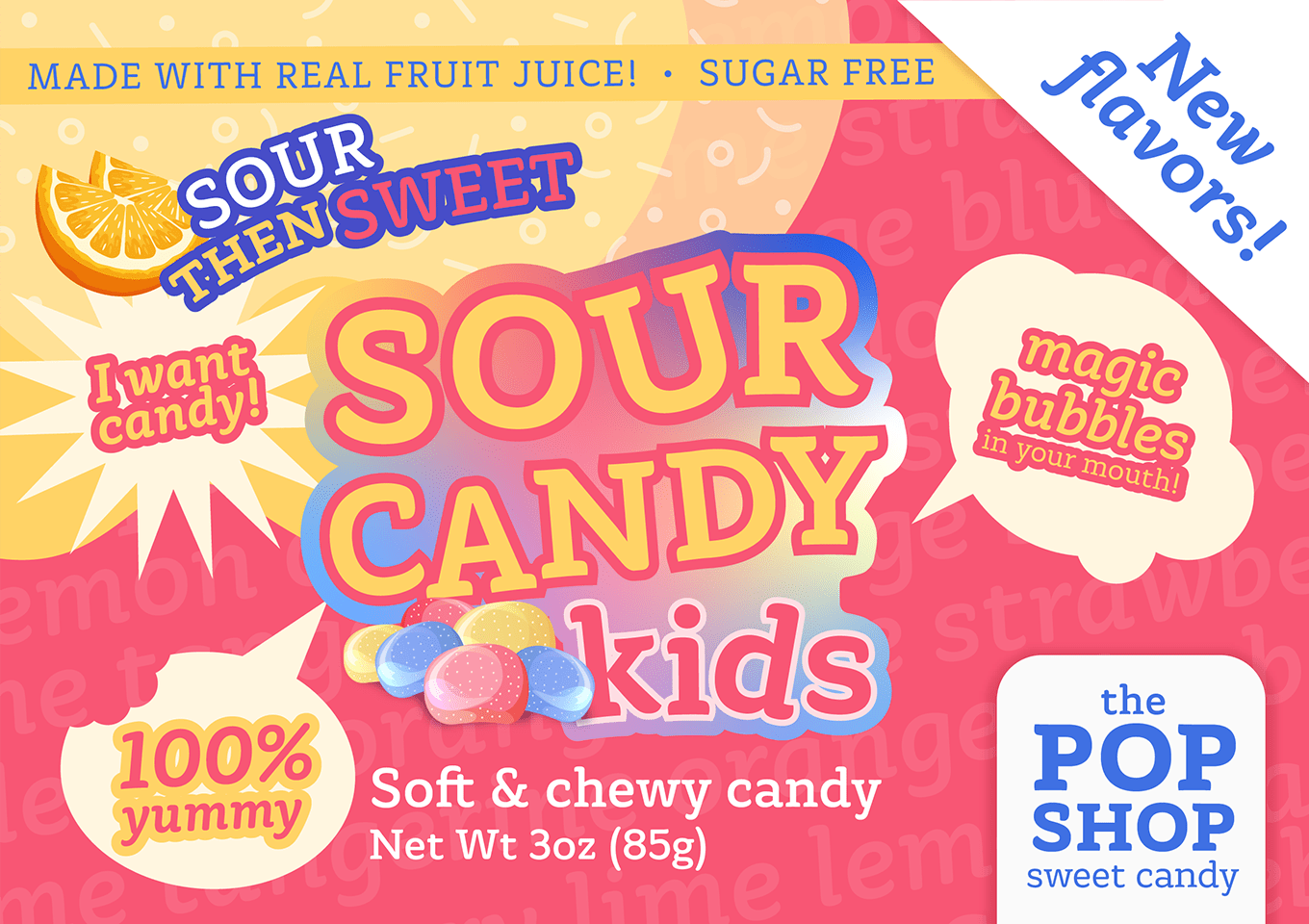
あたたかみのあるカジュアルな印象のセリフ体です。オンスクリーンの使用を想定して設計されており、遊び心がありつつもシンプルなエレメント、広い開口部(アパーチャー)や低いコントラストといった特徴から、小さなサイズでも読みやすい本文組を実現します。 151言語に対応し、ラテンアルファベットだけでなく、キリル文字、ギリシャ文字を収録しています。